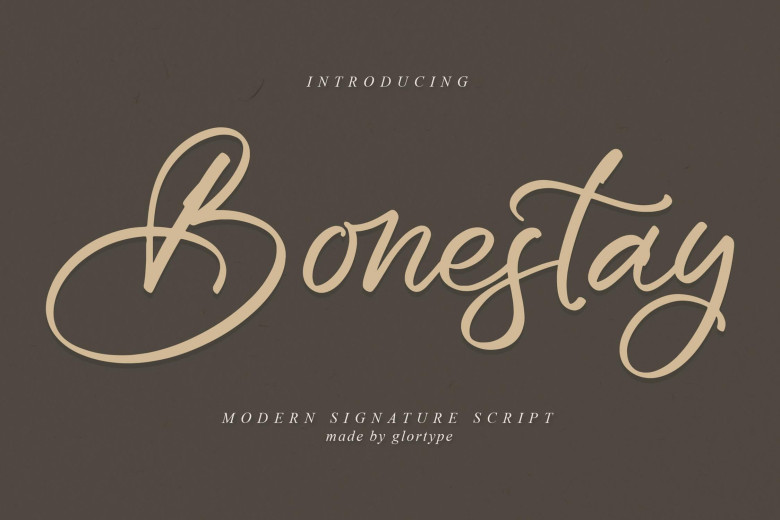
Font chữ viết tay việt hóa Fz Bonestay
Font chữ Fz Bonestay được thiết kế bởi Glorytype Studio và Việt hóa bởi FontZin.
Font chữ này mang phong cách chữ ký hiện đại, mềm mại và đầy tinh tế, phù hợp với nhiều loại thiết kế như:
• Logo, thương hiệu.
• Bao bì sản phẩm, áo thun, cốc, túi xách.
• Thiệp mời, thiệp chúc mừng.
• Bìa sách, poster, hoặc trích dẫn trang trí.
Hình Ảnh demo font viết tay việt hóa Fz Bonestay
Fz Bonestay hỗ trợ tiếng Việt đầy đủ, giúp bạn dễ dàng tạo ra những thiết kế ấn tượng và mang dấu ấn cá nhân. Dưới đây là hình ảnh được thiết kế từ font chữ Fz Bonestay.